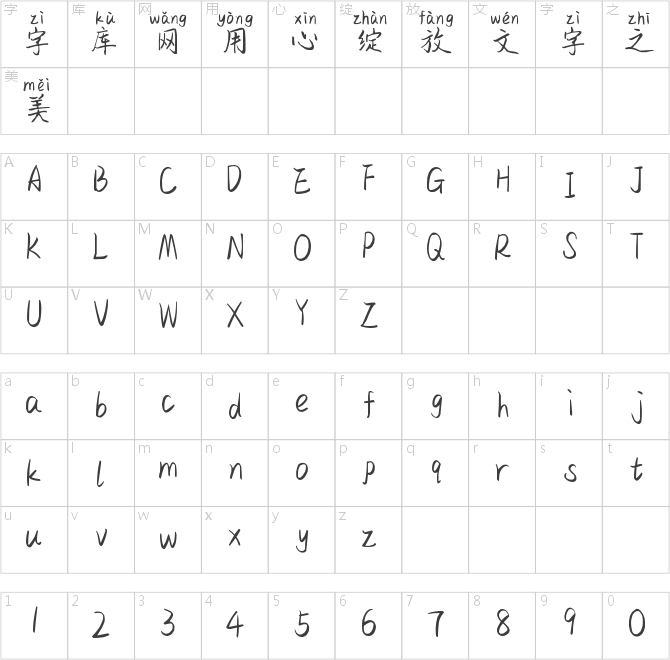
少年且當(dāng)年少
方正手跡
方正
少年且當(dāng)年少字體下載FZSJ-SHAONQDNS
少年且當(dāng)年少是一款添加了拼音的手寫行書體。該字體整體結(jié)構(gòu)穩(wěn)定,筆畫比較舒展延伸,部分筆畫拉出筆鋒使字體更加挺拔有力。該字體適用于文藝類的書刊、品牌廣告和產(chǎn)品包裝設(shè)計(jì),以及社交網(wǎng)絡(luò)的個(gè)性化用字。